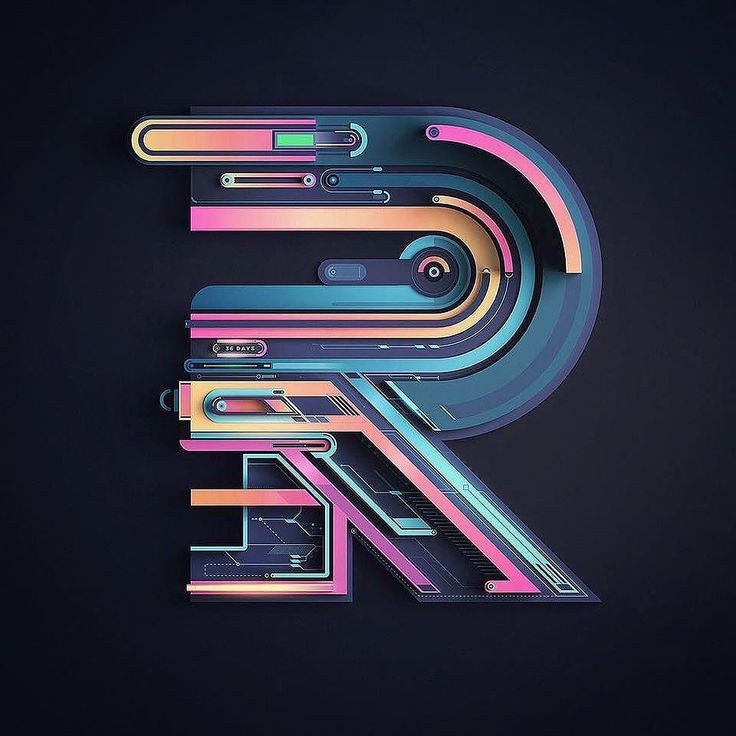
Футуристические шрифты: что это такое и некоторые из лучших примеров
Есть шрифты, которые переносят нас в разные времена и века, например, мы находим некоторые шрифты, такие как римские, которые ведут нас во времена, наполненные боями и гладиаторами, которые сражались и поддерживали очень подчеркнутый классистский стиль. Есть и другие, такие как шрифт без засечек, которые ведут нас к нашему настоящему, приглашают нас увидеть их более четкое изображение и легче идентифицировать.
Но есть еще один стиль, ставший очень модным в последние десятилетия и оставивший след как в мире типографики, так и в мире искусства, особенно в мире художественного авангарда. Стиль, который ведет нас в будущее и возвышает на десять, а то и больше лет вперед.
В этом посте Мы говорим о футуристических шрифтах и как они произвели революцию в концепции искусства, которую мы знаем сегодня.
Кроме того, мы покажем вам несколько примеров лучших футуристических шрифтов, существующих в настоящее время.
Футуризм
Футуризм Это одно из течений и художественных движений последних десятилетий. Его рождение произошло благодаря итальянцу Филиппо Томассо Маринетти, наверняка вы уже знаете его имя, но мало кто знает историю и отношения, существующие между ним и футуризмом.
Прежде всего, вам нужно знать, что футуризм — это одно из движений, возникших с идеей революционизировать и продвигать технологии, это означало великое обновление многих уже существовавших течений, поскольку это движение возникло, чтобы изменить все.
Это было движущей силой многих достижений, включая самолет, автомобиль или промышленные города, которые росли и развивались с течением времени. Словом, движение, которое все разрушило и которое сопровождает нас в настоящем.
общие черты
Его актер
Как уже упоминалось выше, его автор — Филиппо Маринетт, итальянский поэт, который начал движение после создания своей знаменитой поэмы «Слова на свободе».. Его способ писать и интерпретировать все, что он читал, породил движение, способное возглавить фонетическое и визуальное окружение некоторых его произведений.
Завод
Подавляющему большинству футуристических работ свойственна заряженность силой и движением. Они очень динамичны и всегда дают ощущение, что вот-вот оживут. и они порвут со всем вокруг себя. Поскольку это движение предназначено для новых поколений, оно имеет тенденцию быть очень революционным.
Тематический
Как и любое движение, футуризм состоит из различных тем, которые нашли отражение в его работах.
Это темы, связанные с современностью и текущим миром, т. такие аспекты, как города и автомобили, движение и динамичность, некоторые машины, спорт, война и т. д.
Они также используют цвета и шрифты, чтобы придать своим работам больше динамики. Цвета характеризуются определенным свечением, что делает их уникальными цветами, характерными для футуристической эпохи.
футуристические шрифты
свобода и геометрия
Если футуристические шрифты чем-то и характеризуются, то это, несомненно, то, что они были частью движения, которое прорывается сквозь своеобразие и устоявшееся. Вот почему шрифты начинают приобретать более геометрический вид, который показывает исчезновение старого и вид всего, что грядет.
Большинство этих геометрических шрифтов, как правило, представляют собой шрифты без засечек. поскольку засечки обеспечивают более классический и неоднозначный стиль. Короче говоря, футуристические шрифты отличаются своим новаторским внешним видом.
форма и размер
Если мы уверены в одном, так это в том, что у футуристических шрифтов есть особенности, которые имеют высокую контрастность в их внешнем виде. Именно поэтому при его создании большое значение придавалось форме и размеру.. Этот контраст был задуман с целью привлечь внимание зрителя и покорить его взглядом.
Короче говоря, если мы посмотрим на футуристические шрифты, мы придем к выводу, что они настолько характерны благодаря тому, как они были разработаны и для чего они были разработаны. Кроме того, их форма — это еще не все, что удерживает их вместе.
Цель
Белое пространство известно как контраст, о котором мы упоминали ранее. Это пространство происходит от влияния, которое русские имели во время войны. Давайте помнить, что многие движения возникли из-за социальных и политических изменений, которые позволили возродиться новым идеям и новым способам рассказать о том, что происходило в то время, через искусство.
Кодистар
Codystar — это семейство двух шрифтов, в котором буквы и символы полностью состоят из точек. Необычный и самобытный, тем не менее, он легко читается.
Исландский футуристический шрифт
Бесплатный шрифт Iceland — сильный шрифт. Будучи широкими и короткими, символы выглядят почти квадратными, больший интерес создают угловые вырезы под углом 45 градусов, которые закругляют края.